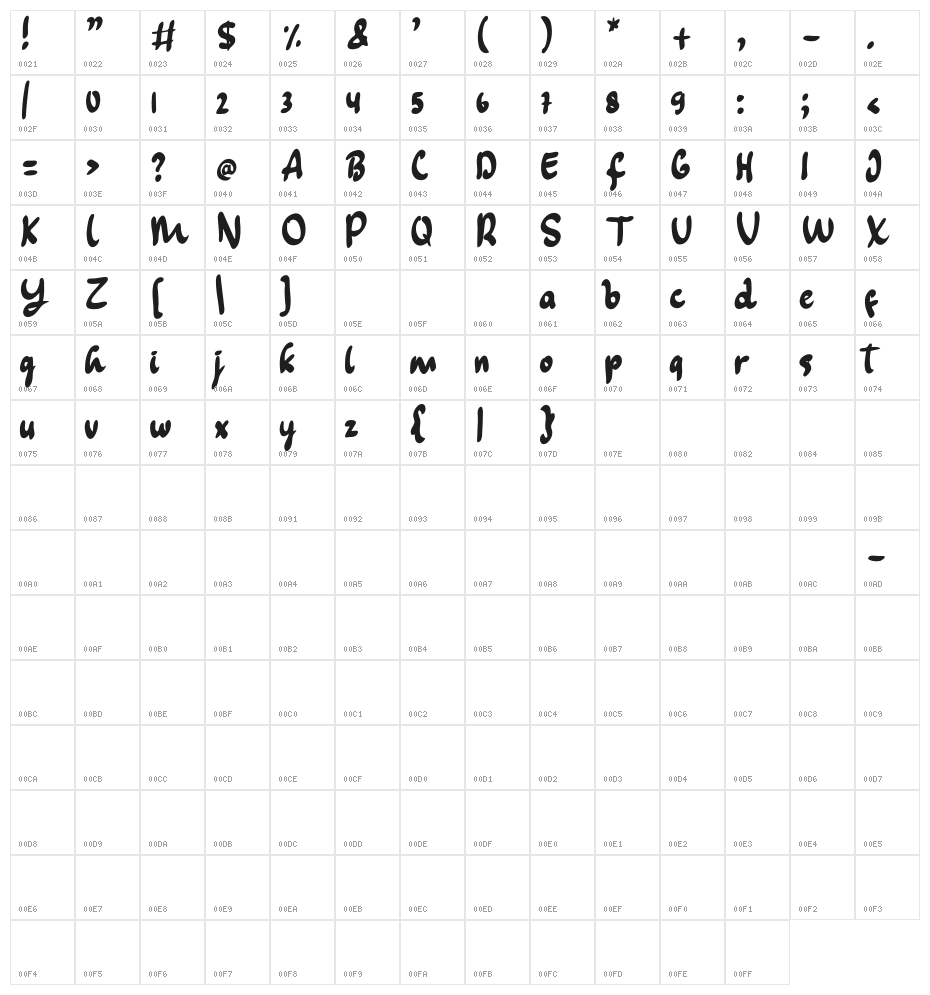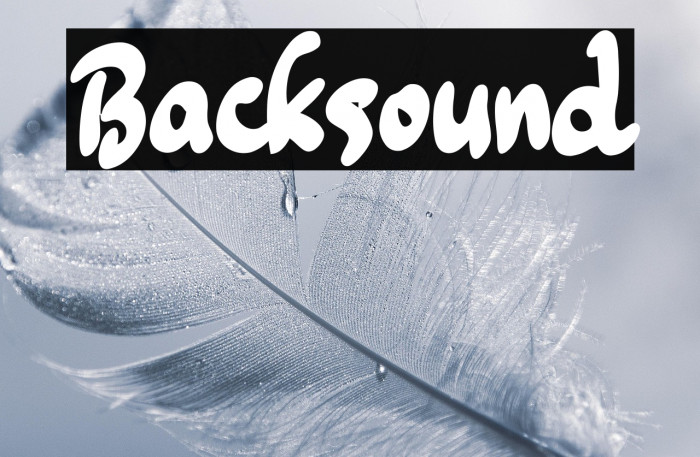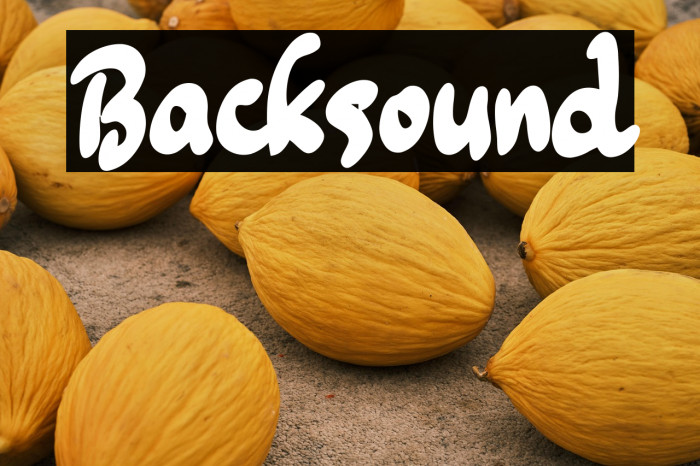
Backsound Font
| Gesamtstil | Playful |
| Anwendungsfall | Logos, Headlines, Informal Text |
| Vorgeschlagene Projekte | Ideal for greeting cards, playful branding, children's books, and casual invitations. |